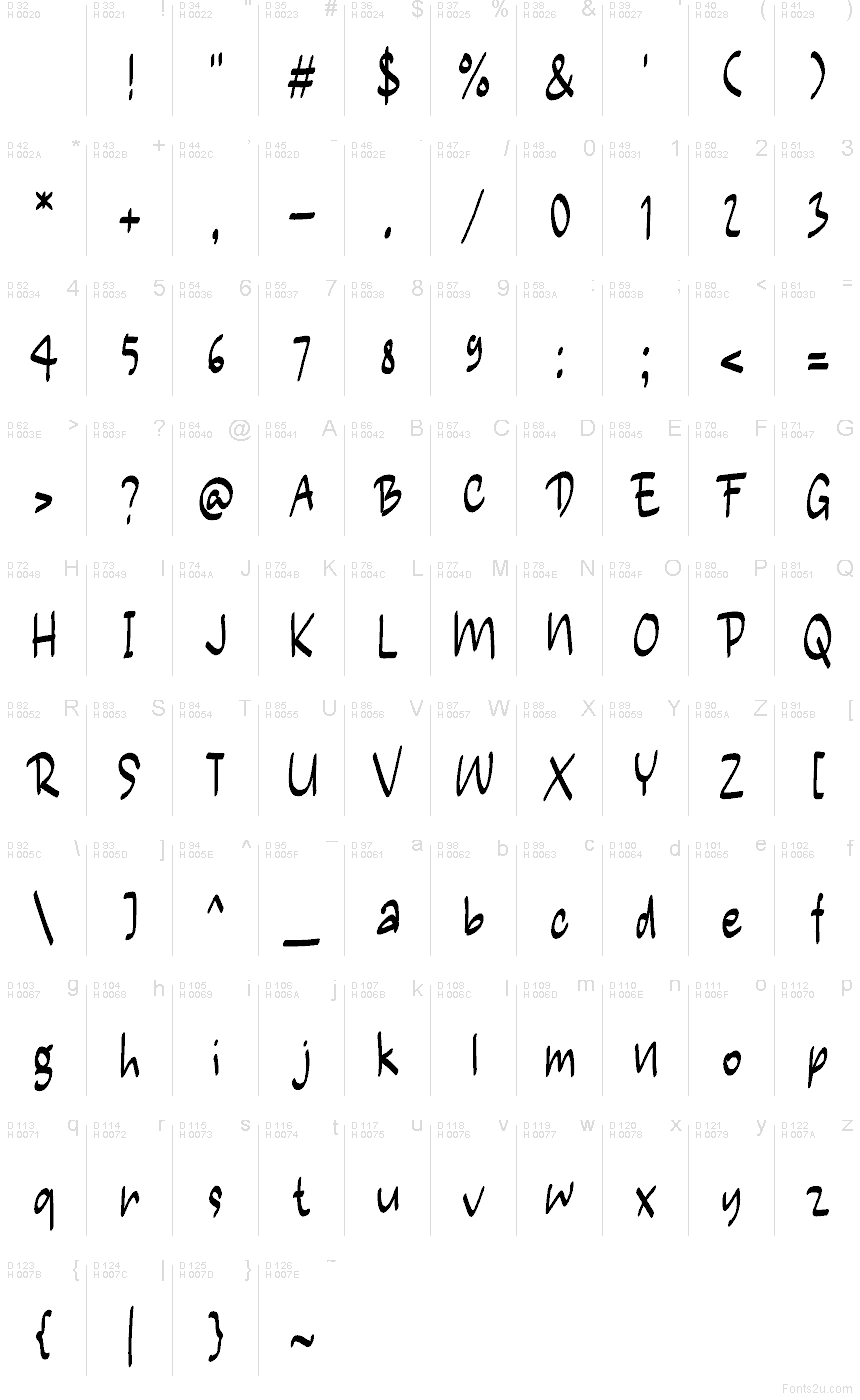
Child Wep
Шрифт Child Wep від Hello Good Studio - це безкоштовний рукописний шрифт з високими, вузькими штрихами та вільним, індивідуальним ритмом. Літери промальовані з м'якими вигинами, закругленими кінчиками та легкою нерівністю, що надає написам невимушеного, а не строгого вигляду.
Цей безкоштовний шрифт чудово підходить для дитячого брендингу, листівок, графіки з цитатами, плакатів, оформлення соціальних мереж та пакування товарів, де потрібен рукописний акцент. Child Wep додає природності коротким заголовкам та декоративному тексту, коли доброзичливий стиль шрифту доречніший за формальну типографіку.